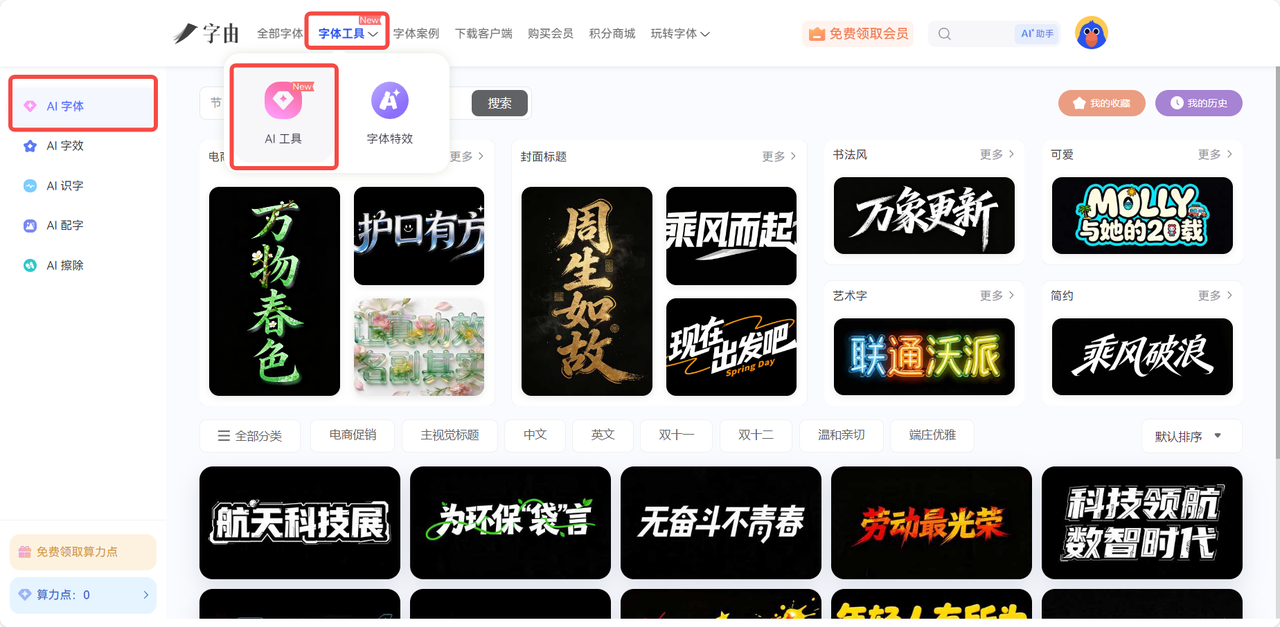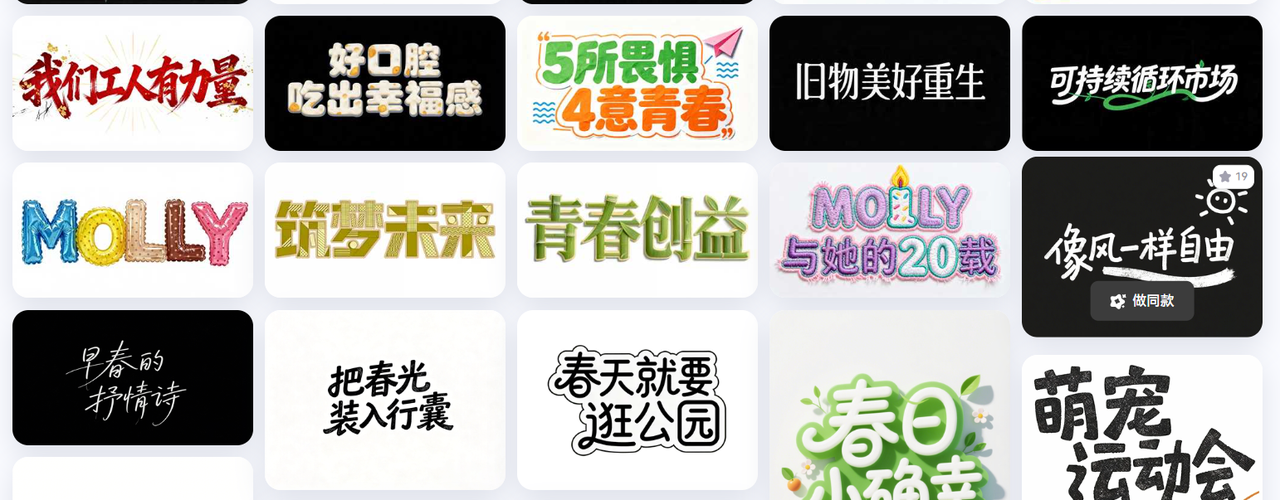
字体生成器在线使用:免费无广告, 多风格字体一键转换
优质且好看的字体对任何作品来说都是加分项,找遍全网的字体平台,或许都没有一个令你满意的字体,还有可能在过程中遇到各种广告弹窗,字体还会面临侵权风险?这时候就需要一个免费无广告的在线字体生成器了!经过我的多次尝试,以及周围设计师朋友们的亲身体验,字由完美解决了这些问题,它字体资源丰富,风格多样,涵盖大部分场景,拥有强大的 AI 字体功能,无需下载安装,就可以一键生成心仪字体。字由的出现,无疑是字体设计领域权威的存在,满足各类用户的创作需求,大大提升字体生成的效率!
一、为什么要选择字由来生成字体?
在众多的在线字体工具当中,字由是我目前使用体验感最好的一款。
首先,它没有任何的弹窗广告,不会因为误触就跳转到其他页面;也没有任何捆绑下载的设计,用户在这里可以只获取到自己想要的东西。
其次,字由的功能非常丰富,拥有海量字体资源和字体特效、AI工具(AI字体、AI字效、AI识字、AI配字、AI擦除)、支持一键切换字体、支持上传个人与团队云字库、个性化分组、字体收藏、多终端登录云端自动同步。
二、字由怎么在线生成字体
字由的 AI 字体功能是在线生成字体的核心公布能,操作流程简单高效,一键转换字体风格,新手小白也嫩恶搞快速上手,具体步骤如下:
1.打开字体功能页面
登录字由官网,在上方菜单栏点击【字体工具】—【AI 字体】,也可以直接访问 https://www.hellofont.cn/font-design-ai 进入AI 字体功能,页面布局非常清晰。
2.按需筛选字体风格
字由按照语言、场景、风格对这些字体进行了详细的分类,按照你的需求进行筛选,确定自己想要的字体。
按照场景筛选:海报、社交媒体、艺术签名、餐饮、电商、优惠券、游戏标题等。
按照风格筛选:端庄优雅、有趣、涂鸦、科技感、复古、中国风、艺术字、渐变等。
3.实时预览文字效果
选中你心仪的字体之后,在文本内容框输入自己需要的文字,点击【立即生成】,等待 30s 左右就可以生成字体了。不满意的的话可以随时调整,再次生成。
4.下载与使用
生成的字体达到你的要求之后,可以选择保留原背景还是透明背景,一般来讲透明背景会比较适合后续的设计。点击下载,字由会自动将字体存为 PNG 格式,方便直接应用到其他设计软件中。
三、字由可以生成哪些类型的字体?
1.社交配图:打造吸睛文案
日常发朋友圈、小红书、微博、ins 等社交媒体,有时候觉得自己的图片缺点东西,选择一款好看的字体能直接影响点击率。如果是节日相关的社交媒体,可以直接搜索对应的节日名称;如果是是萌宠类的配图,可以直接筛选可爱、卡通这种类型。
2. 电商促销:提升用户购买力
电商促销的版块是字体风格最多的,我们经常会在刷手机的时候看到某个电商平台的满减活动而点进去,前提是这个活动页面的文字足够醒目且吸引人。字由的 AI 字体完全可以帮助你快速生成电商促销风格的字体,不管是年货节、双十一、双十二,还是季末大促、现实抢购、新品首发,你都可以直接筛选定位到对应的版块,然后再选择合适的字体。
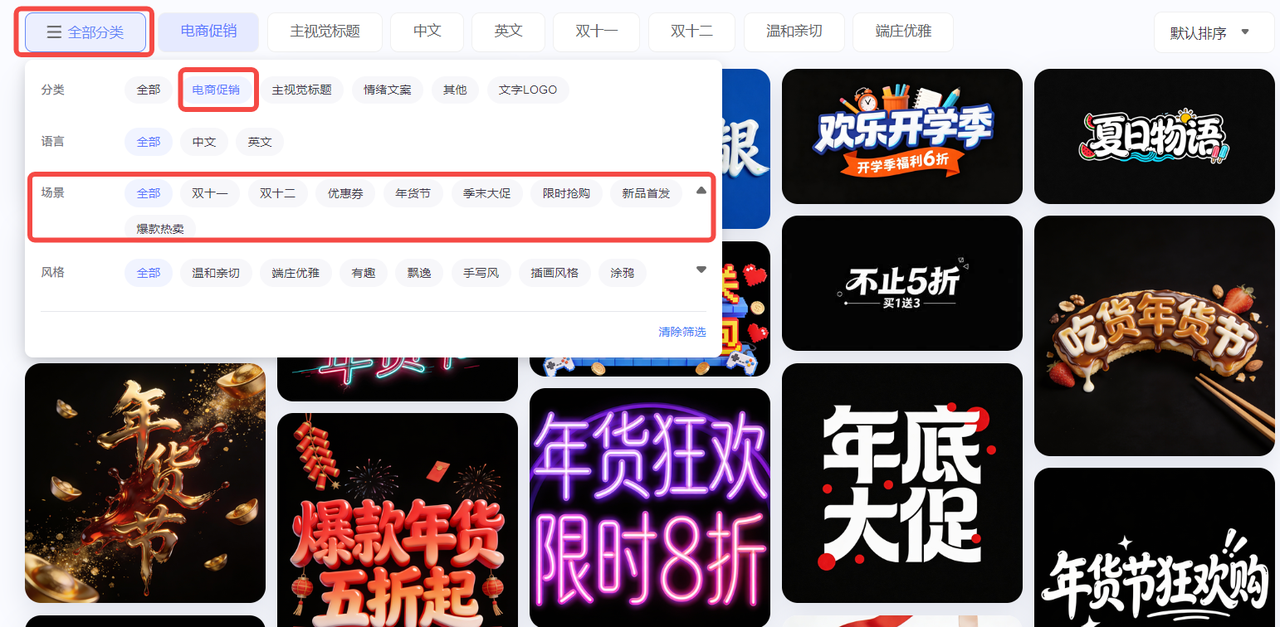
3.海报设计:突出主题氛围
活动海报、节日海报需要字体风格与主题呼应。比如新年海报会用一些红色黄色作为主色调;科技活动的海报字体风格会更酷炫;毕业季海报经常用手写风;展览类海报会选择浅色系中国风字体。输入相应的海报标题之后,实时预览字体,就可以快速完成海报标题设计。
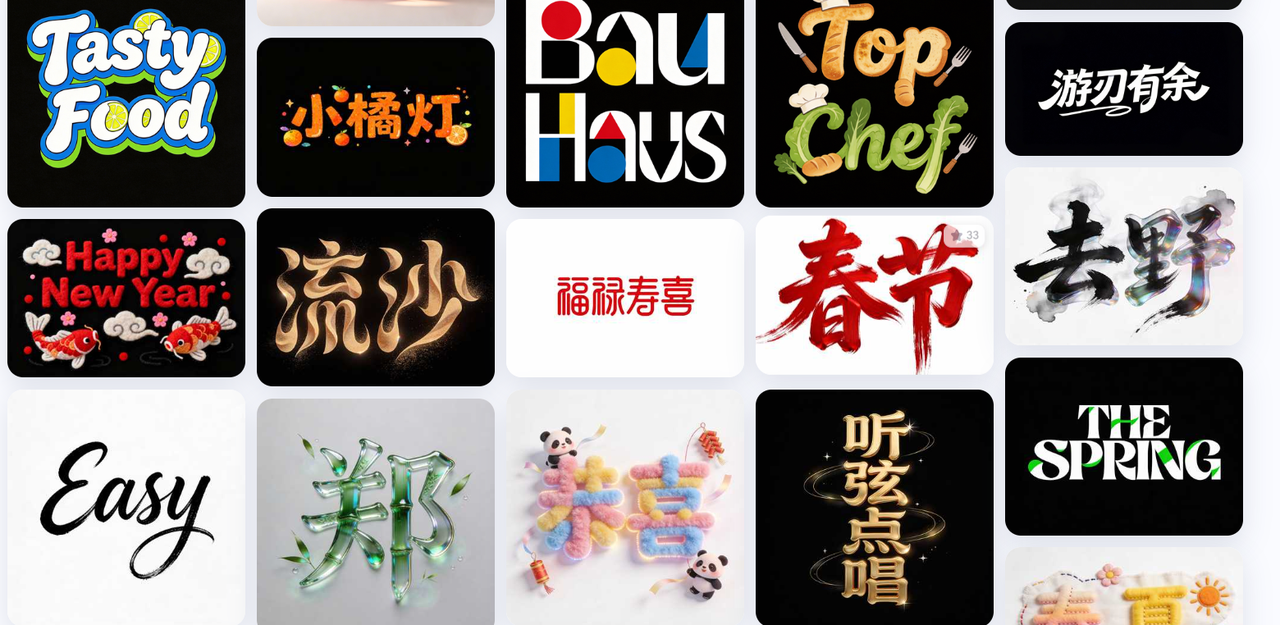
4.艺术签名:满足个性化需求
字由还有专门的艺术签名字体,如果你也在为设计一个独一无二的签名而头疼,可以来字由试试。不需要你花钱找人设计,30s就能搞定一个艺术签名,而且涵盖多种字体风格,总有一款能戳中你。
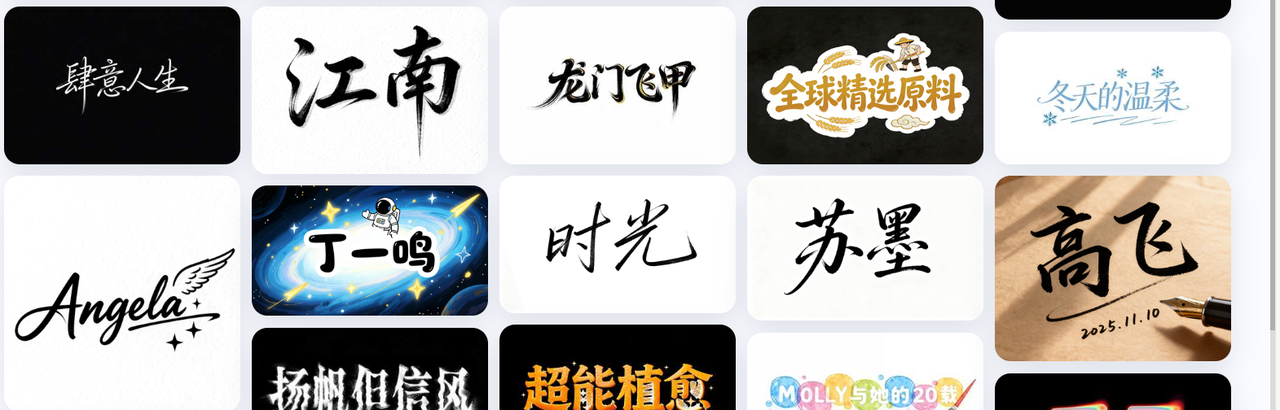
四、字体生成小技巧
1. 搭配字体美化与样式调整
想要拥有一个高级感且吸引人眼球的字体,生成字体的时候还要考虑多方面的因素:
颜色搭配:根据设计场景选择互补色,比如蓝色背景配白色字体;或选择同色系,比如粉色背景配浅紫色字体。
阴影与描边:可以选择一些添加轻微阴影或者描边的字体,比如海报标题这一类就适合有一些轻微的阴影。
文字排版:生成的字体保存下载之后,在设计过程中要注意调整字间距与行间距,提升用户可读性。
综上所述,选择一个合适且好用的字体生成器会让你的设计之路更加通顺,创意更自由!在众多的字体生成器当中,字由凭借“风格多样化、一键生成字体、AI功能强大、免费无广告”这些核心优势,成为很多用户的首选在线字体工具。无论你是想要专业的商业海报、或者是精美吸睛的页面,打开字由官网,进入 AI 字体功能页面,就能在线生成不同风格的字体,感兴趣的小伙伴可以来试一试哦。